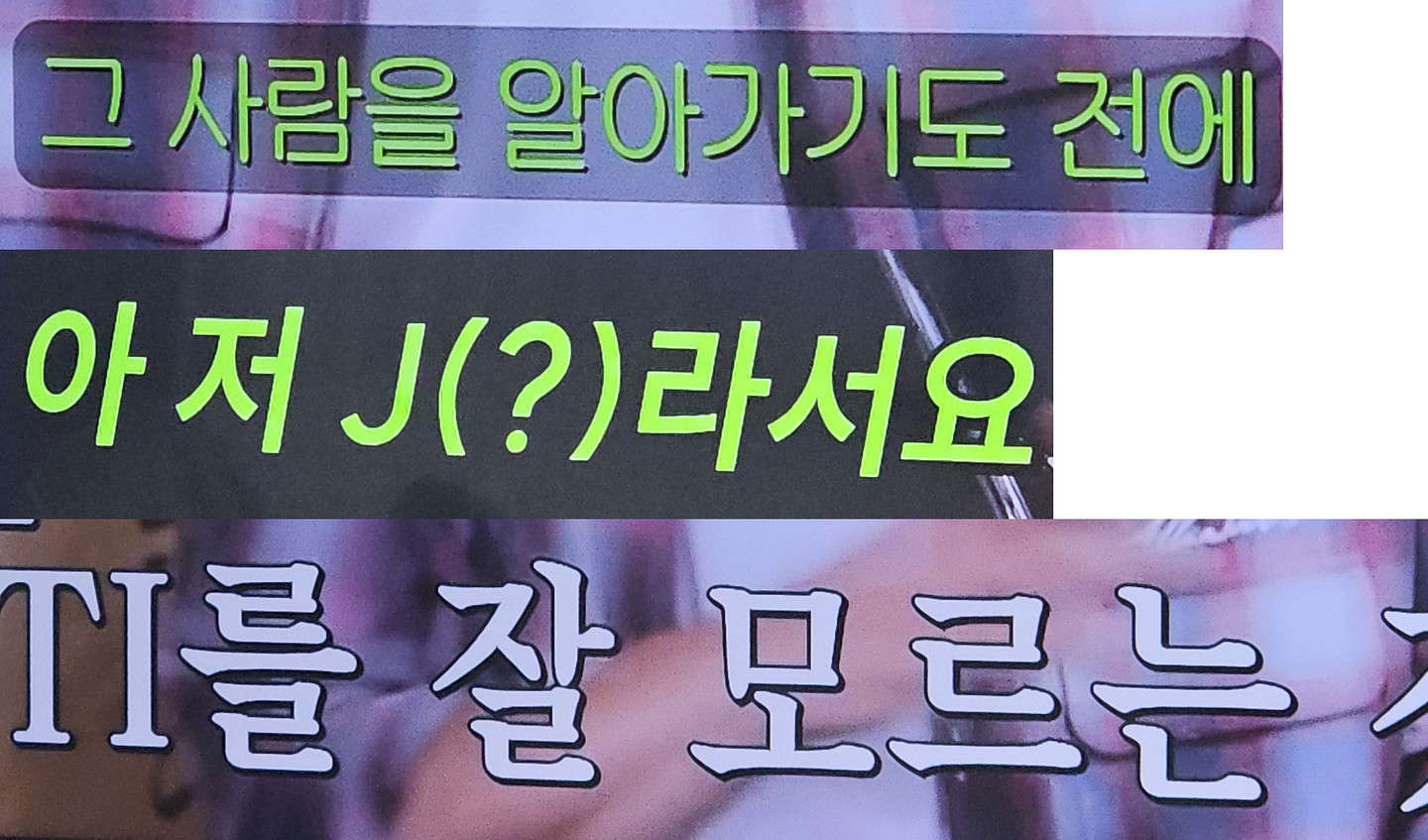
시옷이 산처럼 뻗침없이 한 붓에 쓰였고 리을이 영어 Z처럼 쓰여있습니다. 폰트 ai에 찾아보아도 비슷한 폰트조차 나오지 않네요 ㅠㅠ 혹시 이 폰트의 이름을 알고 계시거나 위에 작성한 것과 같이(시옷과 리을) 비슷한 특징을 가진 폰트를 아신다면 답변 부탁드립니다! (원본 링크 : http://www.clipartkorea.co.kr/search/preview.php?cont_code=ti375a14805&menu=membership&ska=2&_fu=main&keyword=%EC%84%B8%EC%9D%BC&page=80&single_movie_themetitle=undefined&_usl=1&rows=1&TOTAL_PAGE=98539)